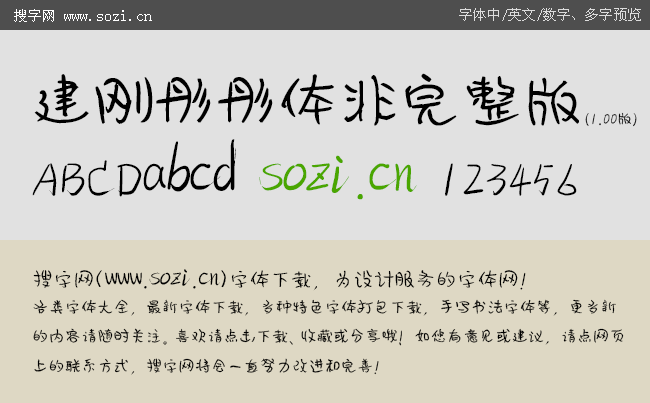
建剛彤彤體非完整版
搜字網(wǎng)提供一款建剛彤彤體中文藝術(shù)字體下載,建剛彤彤體是一款帶有手寫風(fēng)格的中文藝術(shù)字體,線條卡通感很強(qiáng),整體效果非常不錯(cuò),可以應(yīng)用于廣告設(shè)計(jì)、名片設(shè)計(jì)、包裝印刷、產(chǎn)品設(shè)計(jì)等方面,有喜歡的朋友可免費(fèi)下載收藏。